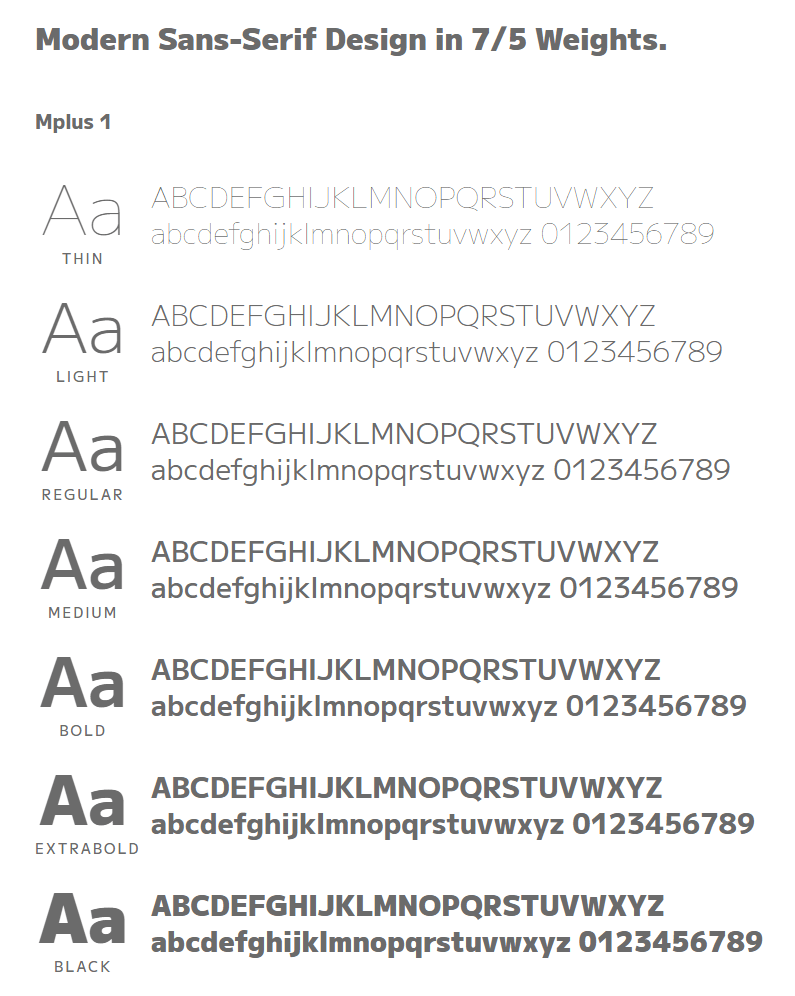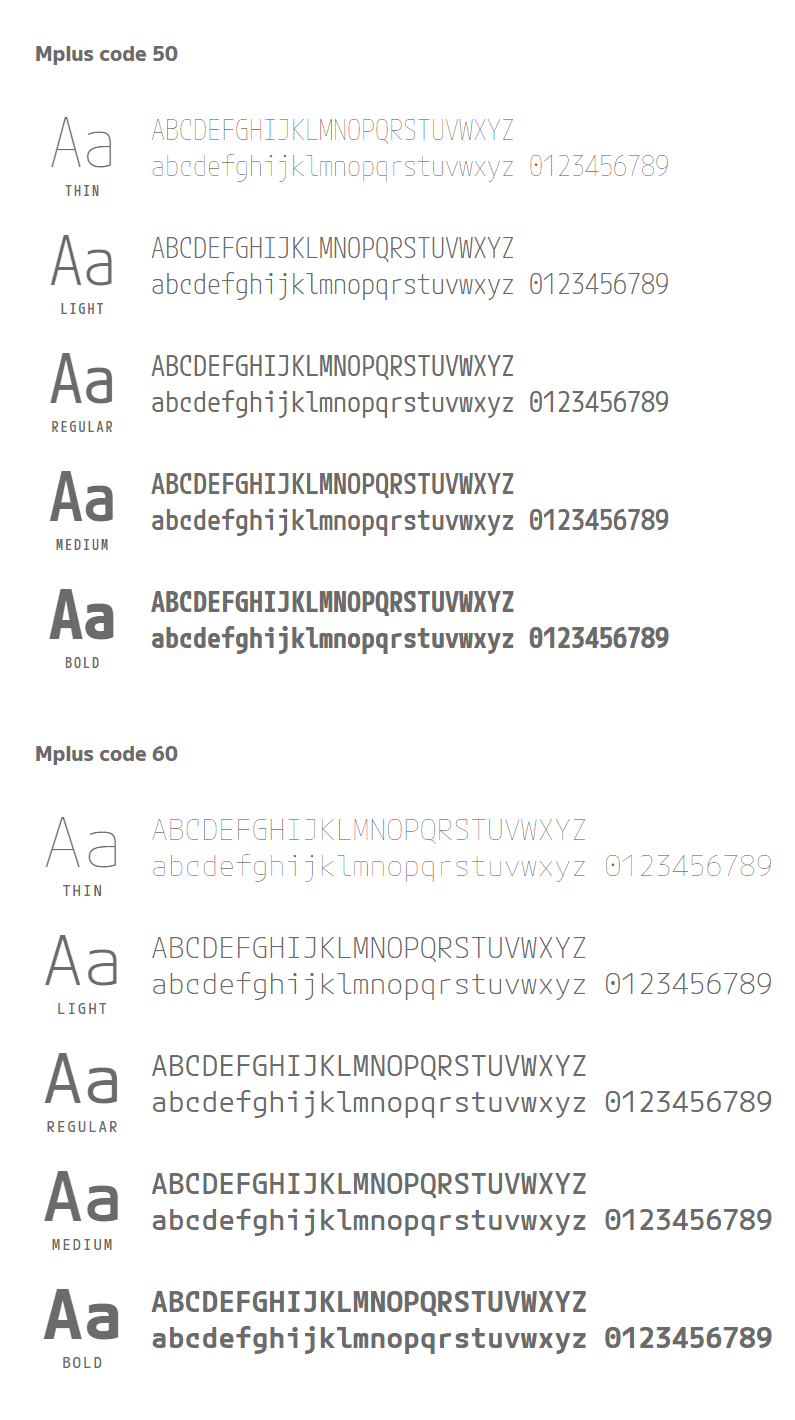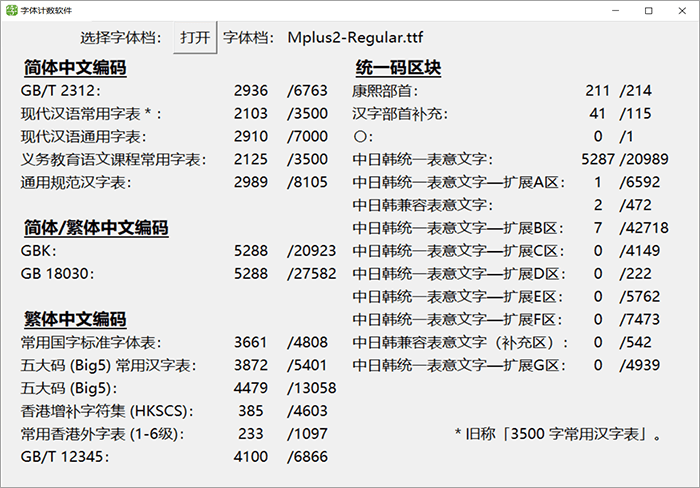
字体介绍
M+FONTS发布于2003年,至今已经历18年。而今,M+FONTS发布M+2版本,并新增了可变字形,并把字体以OFL授权释出。M+FONTS已经将其开发环境迁移到GitHub。OSDN上没有新的更新。旧的信息和字体文件可以在下面的“OSDN”链接中找到,但也请参阅新的“GitHub”版本。
在谷歌的支持下正在修改字体设计。现在,GF Latin Plus欧文文字组等文字组合了以前的汉字,Mplus1和Mplus2,并且Mplus code字体暂定公开中。新的文字设计也显示在现在看到的这个字体上。
M+ FONTS发布M+2,并把项目迁至GitHub上发布,并把授权更改成OFL授权。
M+ FONTS第一版正式发布